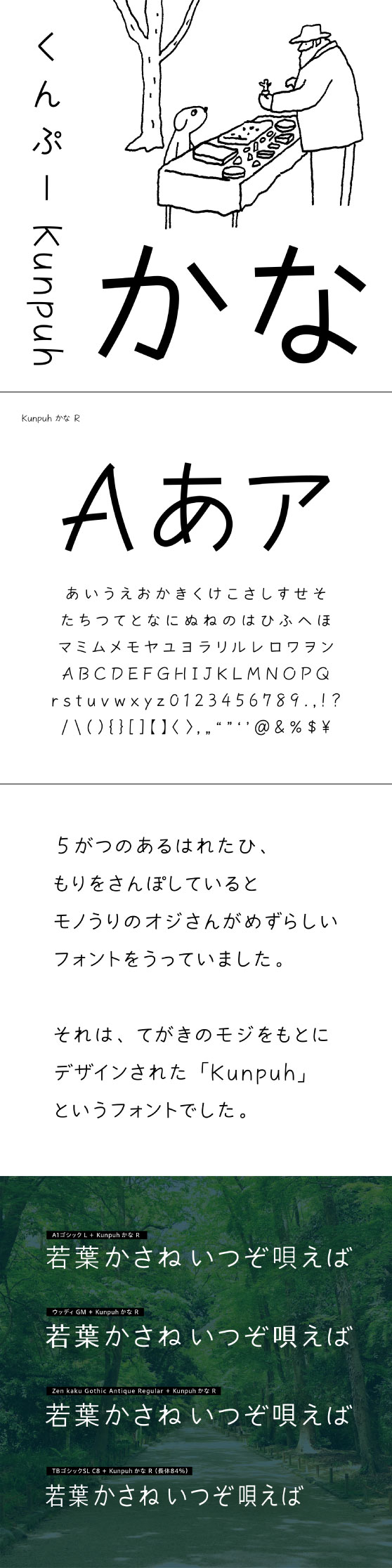
手書き風書体
Kunpuh かな R
手書きの文字をベースにデザインされた手書き風かなフォントです。かわいいけれど甘すぎず、伸びやかなストロークとぬけ感の心地よさが特徴。定番フォントとの混植によって話し言葉のような雰囲気を演出できます。
広告のキャッチコピーやロゴ、見出しなどのデザインのワンポイントにオススメです。